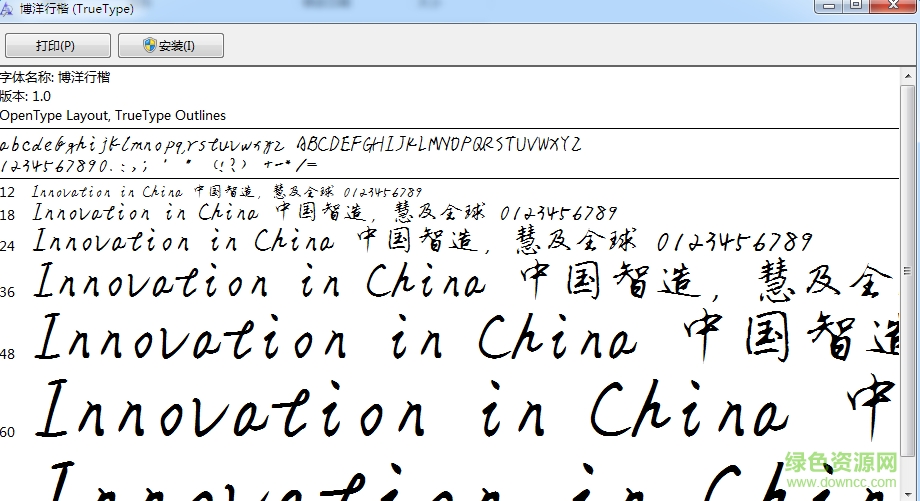
博洋行楷字體是一款非常非常有特色的行楷電腦字體,繼承行楷簡(jiǎn)約書寫筆畫的特點(diǎn),但是同時(shí)保證的自己的清晰和易識(shí)別,有喜歡這款字體的朋友可以來(lái)綠色資源網(wǎng)下載試用!
博洋行楷是一款字形優(yōu)美的漢字行楷手寫體字形,是漢字在楷書基礎(chǔ)上簡(jiǎn)約書寫筆畫、增強(qiáng)書寫映帶、表現(xiàn)書寫意趣以適當(dāng)加快書寫速度的,少量改變書寫筆順,且具較強(qiáng)易識(shí)、易學(xué)特征的實(shí)用性手寫體字體。